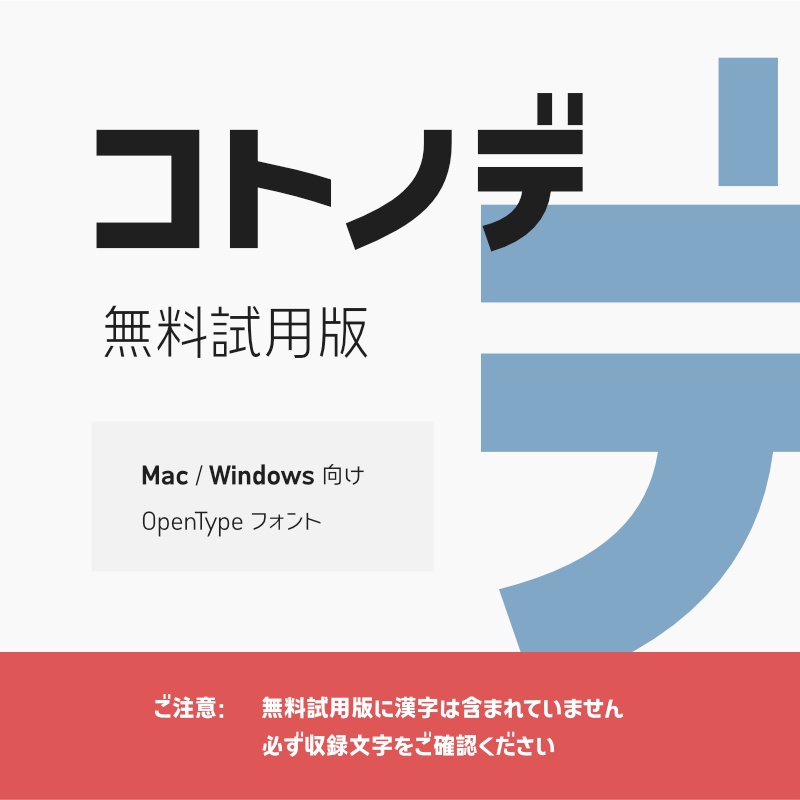
「コトノデ」フォント(無料試用版) ~シンプルで明るい雰囲気のゴシック体~
このフォントは、「コトノデ」「コトノル」「コトノモ」などのシリーズのフォントの動作を確認するための無料試用版です。 もっとも太いウェイトの「Black」のみの収録となっており、漢字は収録しておりません。 ※無料試用版の商用利用は不可ですが、販売用の同人誌・同人グッズへの利用に限っては可能となります(BOOTHでダウンロードするコトノデ無料試用版フォントのみ)。 漢字付きの各フォントについては、以下のページからアクセスしてください。 【コトノハワークスの制作フォント一覧】 https://kotonohaworks.com/fonts.html
・無料試用版に漢字は含まれていません。。 ・通常のフォントよりも上下にはみ出たデザインです。この無料試用版では、濁点や「j」などの文字が、使いたいアプリで見切れて表示されていないかを、「コトノデ」「コトノル」「コトノモ」などの各シリーズのフォントの購入前に確認可能です。 ・公式の紹介ページの利用規約・免責事項を必ず確認してください。 【コトノハワークスの制作フォント一覧】 https://kotonohaworks.com/fonts.html 2024/05/28 ver.3.100 リリース。 2025/03/25 ver.4.105 リリース。 2025/09/08 ver.4.106 リリース。